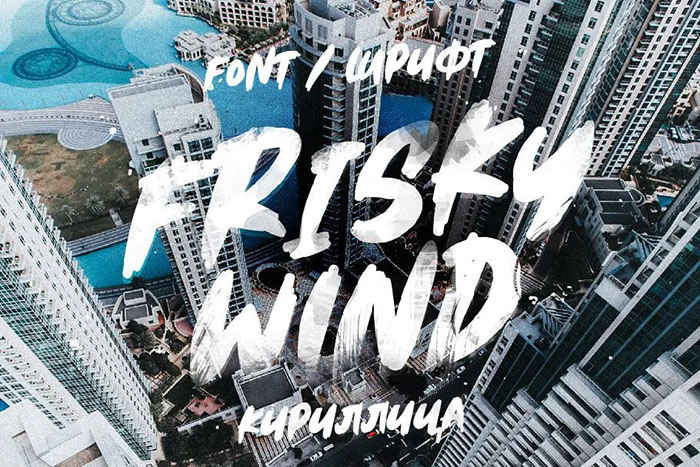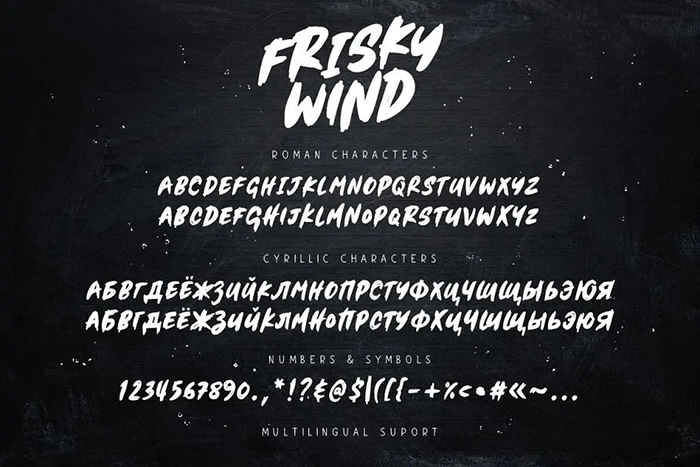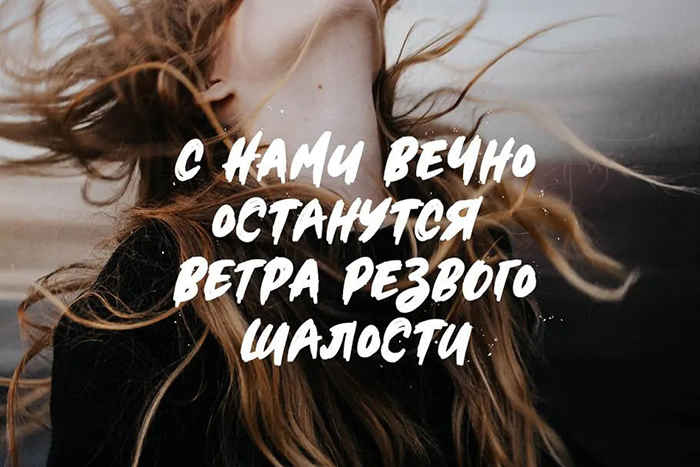
Frisky Wind Font
Font ~ Frisky Wind | Шрифт ~ Резвый ветер
About the product: Резвый ветер (Frisky Wind)
✦ Шрифт, созданный мастерством кисти, который прекрасно гармонирует с логотипами, элегантно оформляет упаковку продукции, украшает футболки своей изысканностью и дарит живое вдохновение для рукописных цитат.